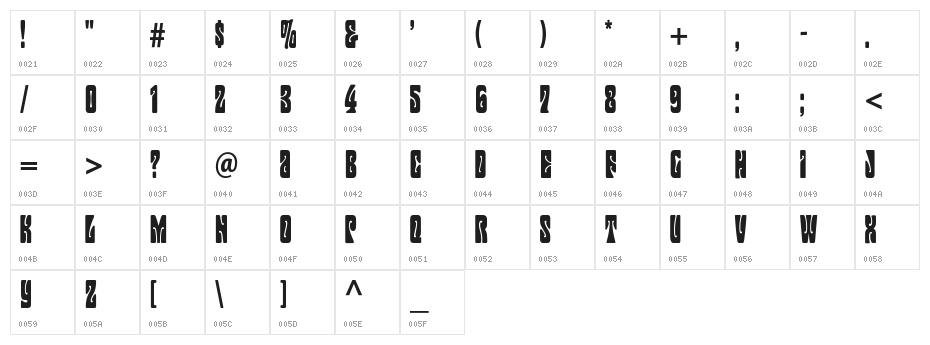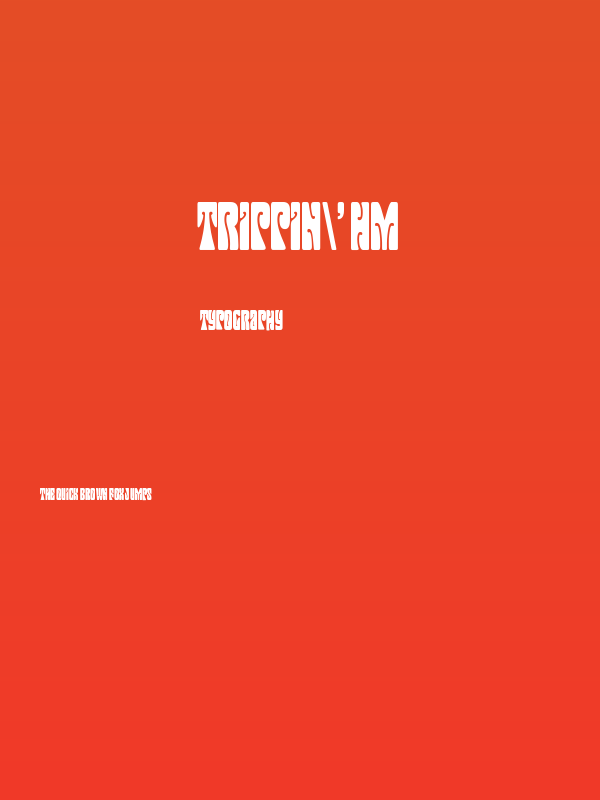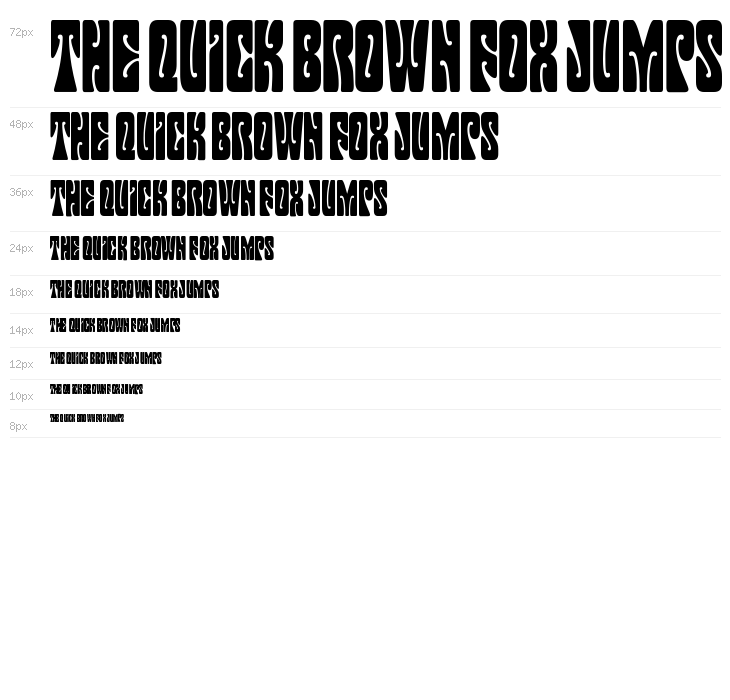
Trippin' HM Font
| Категория | Retro |
| Область применения | Decorative elements, graphic design, modern art. |
| Рекомендуемые проекты | Ideal for use in modern art installations, graphic design projects, or as a decorative element in architectural designs. |